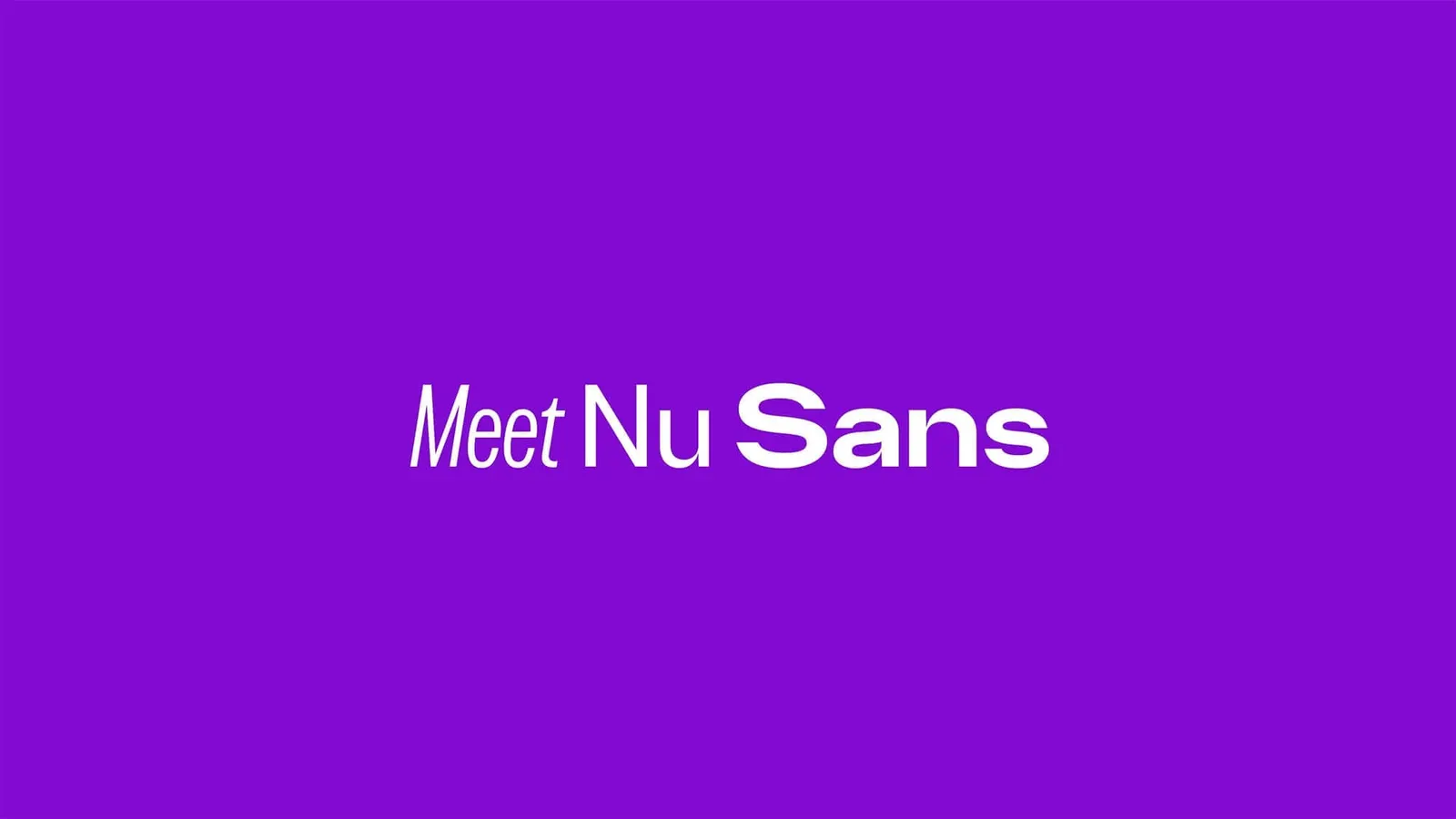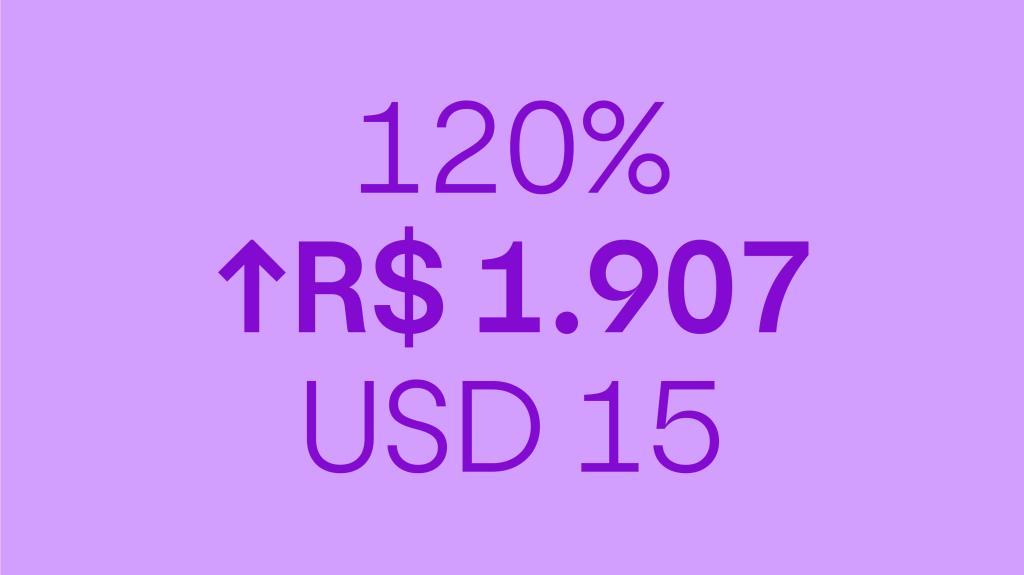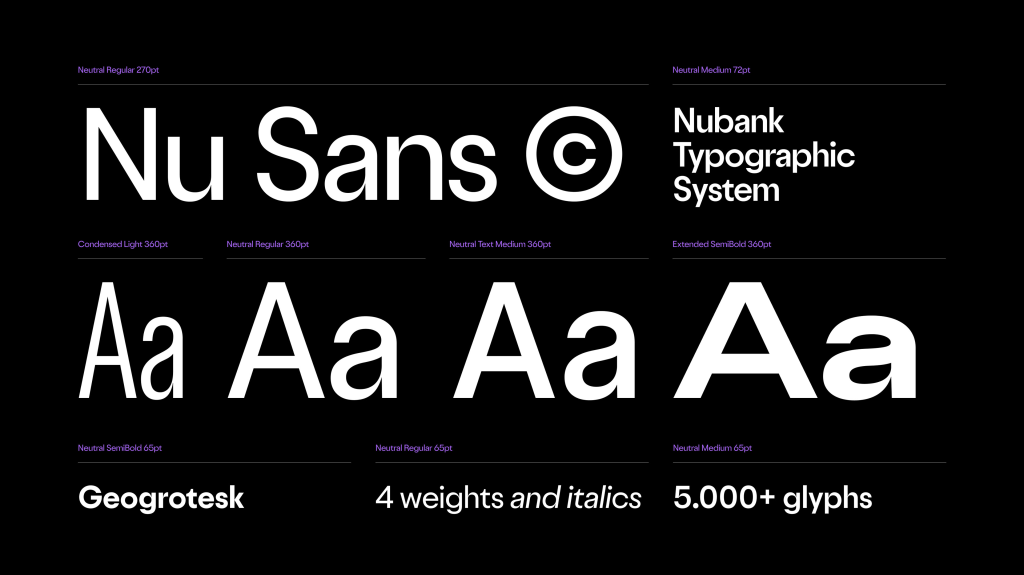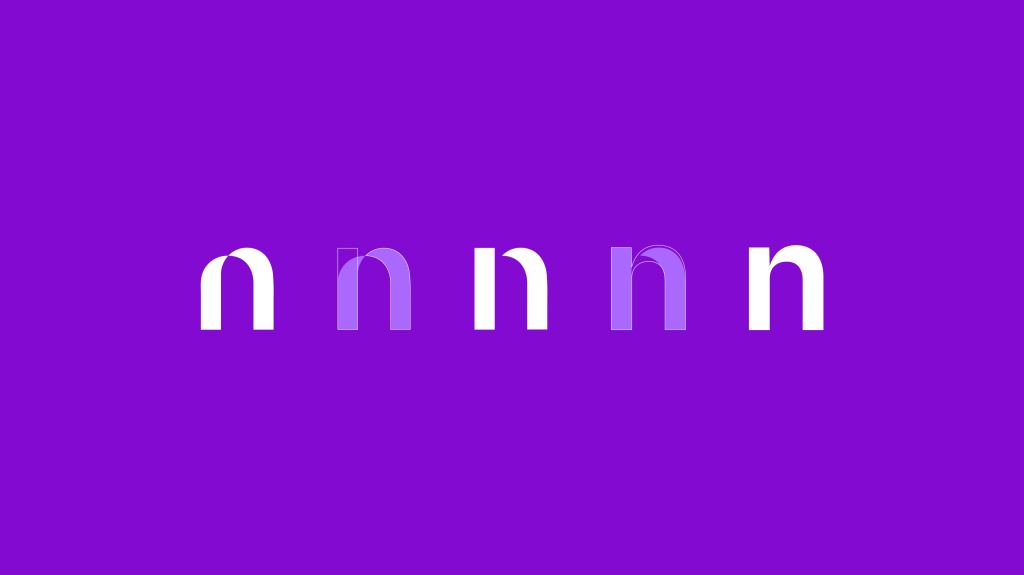
Nubank lança Nu Sans, sua primeira tipografia proprietária com 32 variações
Família tipográfica criada com a Blackletra Type Foundry nasceu do logo da marca e foi desenhada para funcionar como camada de segurança contra fraudes visuais
O Nubank lança a Nu Sans, sua primeira família tipográfica proprietária. São 32 variações de peso e largura, divididas em dois tamanhos óticos (Display para títulos, Text para leitura longa), com suporte a português, espanhol e inglês.
O desenvolvimento levou 14 meses, incluiu pesquisa com funcionários, entrevistas com líderes de áreas diversas e clientes, e foi executado em parceria com a Blackletra Type Foundry. O projeto é liderado pelo time interno de branding, com supervisão de Tiago Lara e da CMO Juliana Roschel.
Por que importa: Tipografia proprietária é o tipo de investimento de marca que a maioria das empresas não faz porque o retorno é invisível para quem não é designer. Mas para um banco digital cujo principal ponto de contato é uma tela de celular, a fonte é, literalmente, a voz da marca. Cada extrato, cada notificação, cada número no app é lido através dela. O Nubank processa bilhões de interações por mês. A tipografia é a interface entre o cliente e seu dinheiro.
O design como decisão de negócio: A Nu Sans não é exercício estético. Foi desenhada a partir de três briefings simultâneos:
Legibilidade como produto: A Nu Sans Text foi calibrada para dados financeiros. Números tabulares (cada dígito ocupa o mesmo espaço) garantem alinhamento perfeito em colunas de valores. Negrito e versões finas ocupam o mesmo espaço para evitar que a interface "pule" quando uma informação ganha destaque. Se você entende seu extrato num piscar de olhos, a tipografia está funcionando.
Migração sem atrito: Trocar a fonte de um app com 131 milhões de usuários é operação delicada. A Nu Sans Text foi desenhada com métricas próximas à tipografia anterior — cada caractere ocupa exatamente o mesmo espaço. A transição acontece sem quebra de layout, sem que o cliente perceba. É engenharia de tipo a serviço de engenharia de software.
Segurança como camada visual: Uma fonte proprietária funciona como assinatura digital. Traços exclusivos e difíceis de replicar dificultam tentativas de fraude visual (phishing, apps falsos, comunicações fraudulentas). Quando você reconhece a Nu Sans, sabe que está em ambiente oficial do Nubank. É tipografia como ferramenta de confiança.
A origem no logo: O desenho parte das curvas do logo da marca, o "laço" entre o N e o U. As formas são orgânicas, não geometricamente rígidas. A intenção é que a tecnologia não pareça fria.
Letras são a menor unidade de marca e a tipografia, talvez, o investimento menos glamouroso do branding. Ainda assim, possivelmente é o mais duradouro.